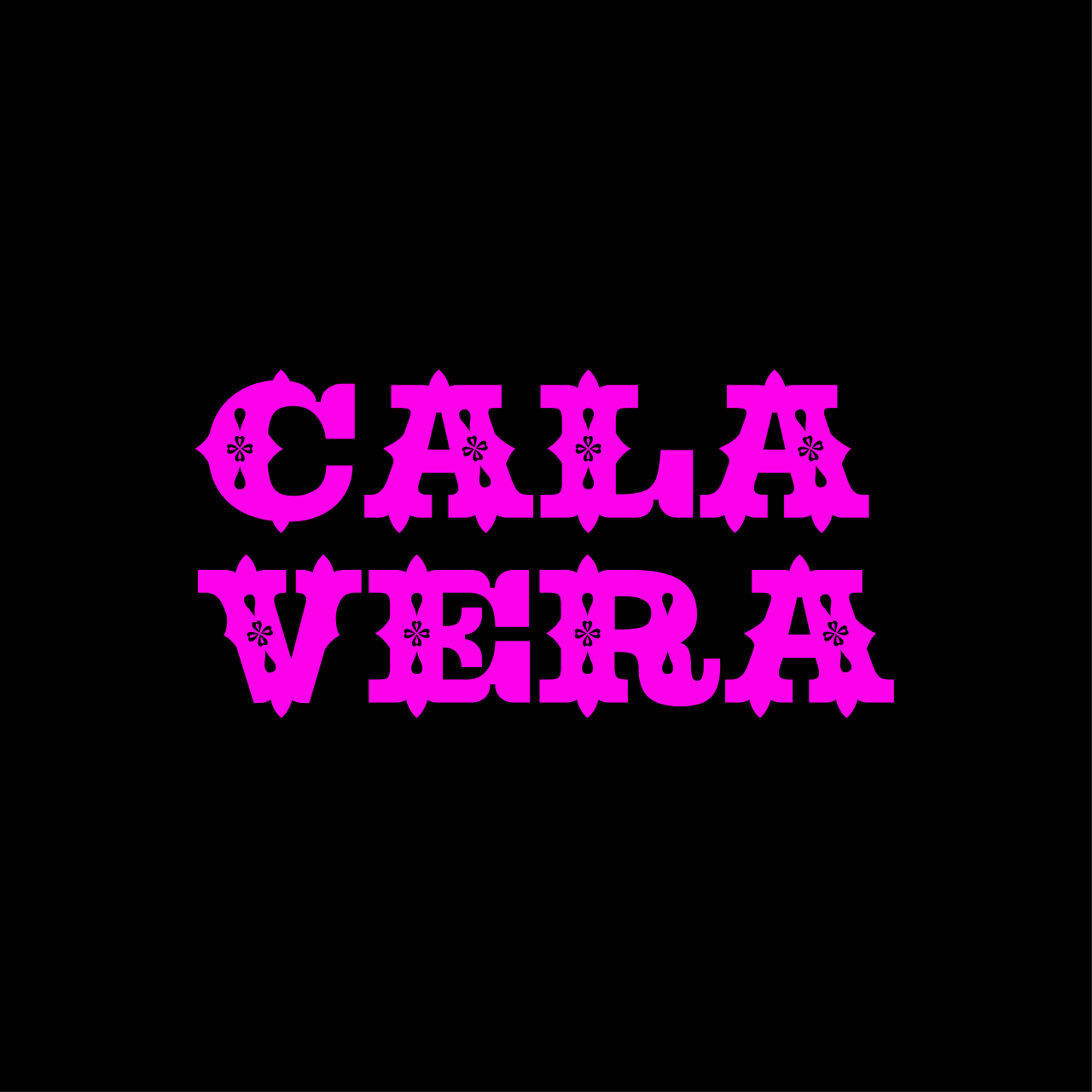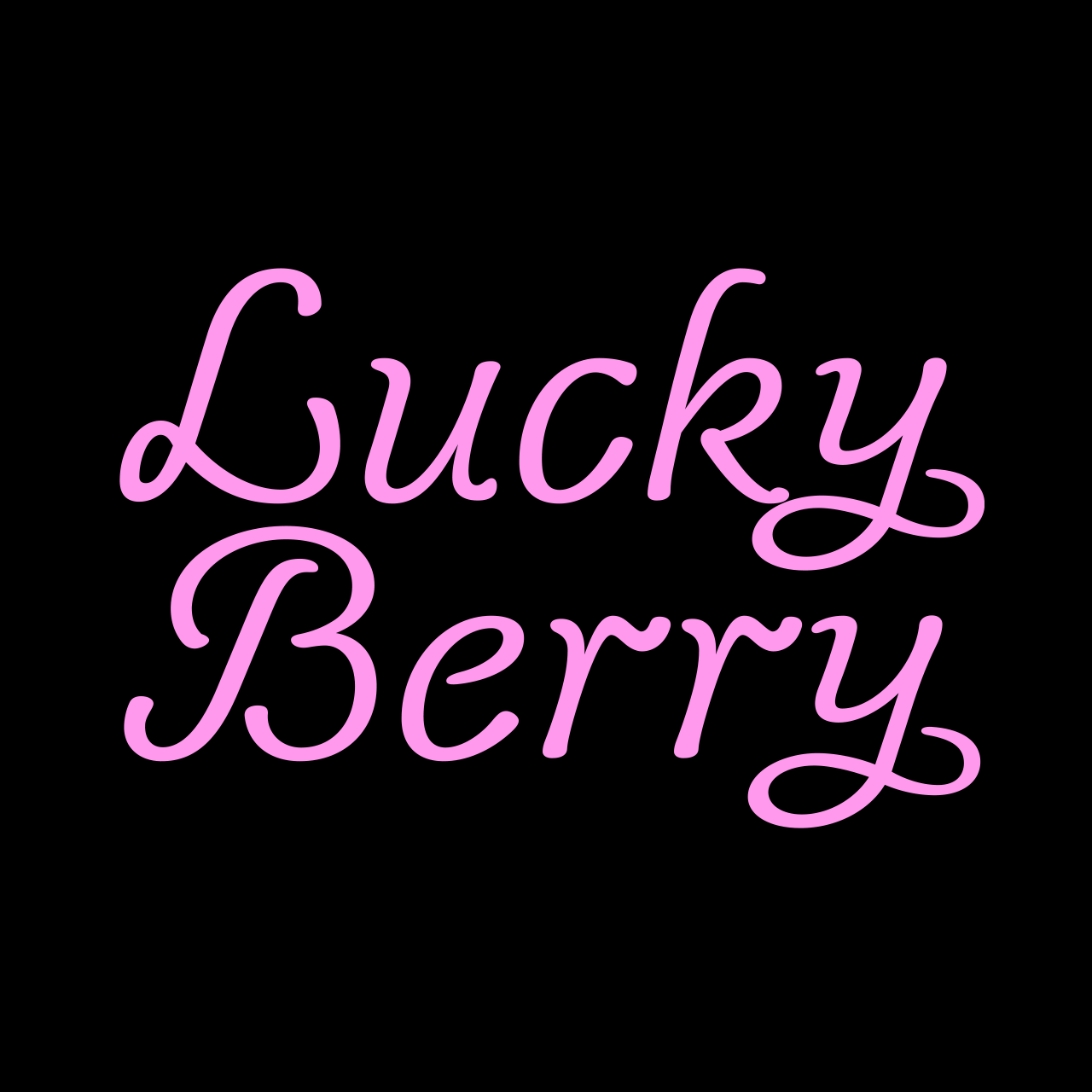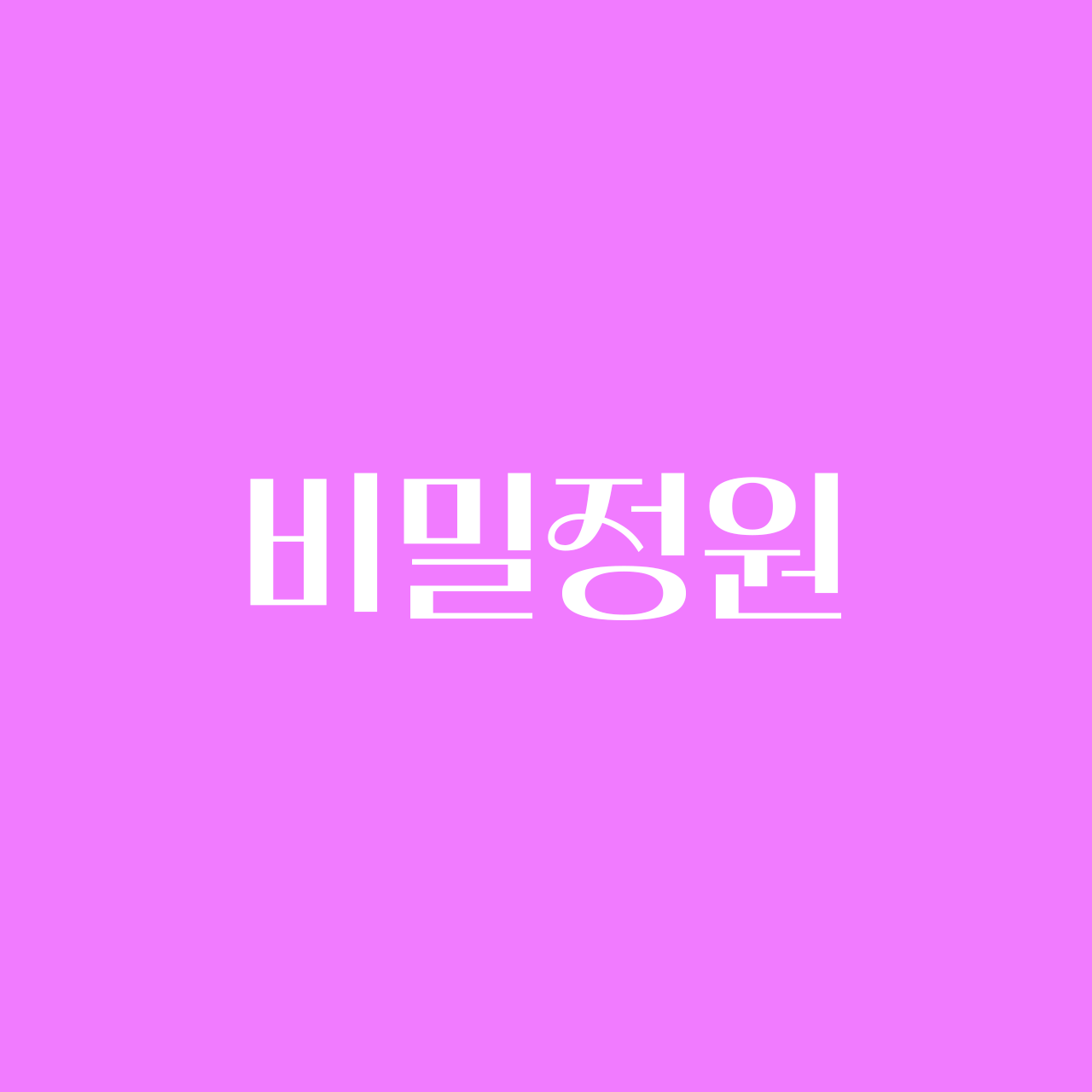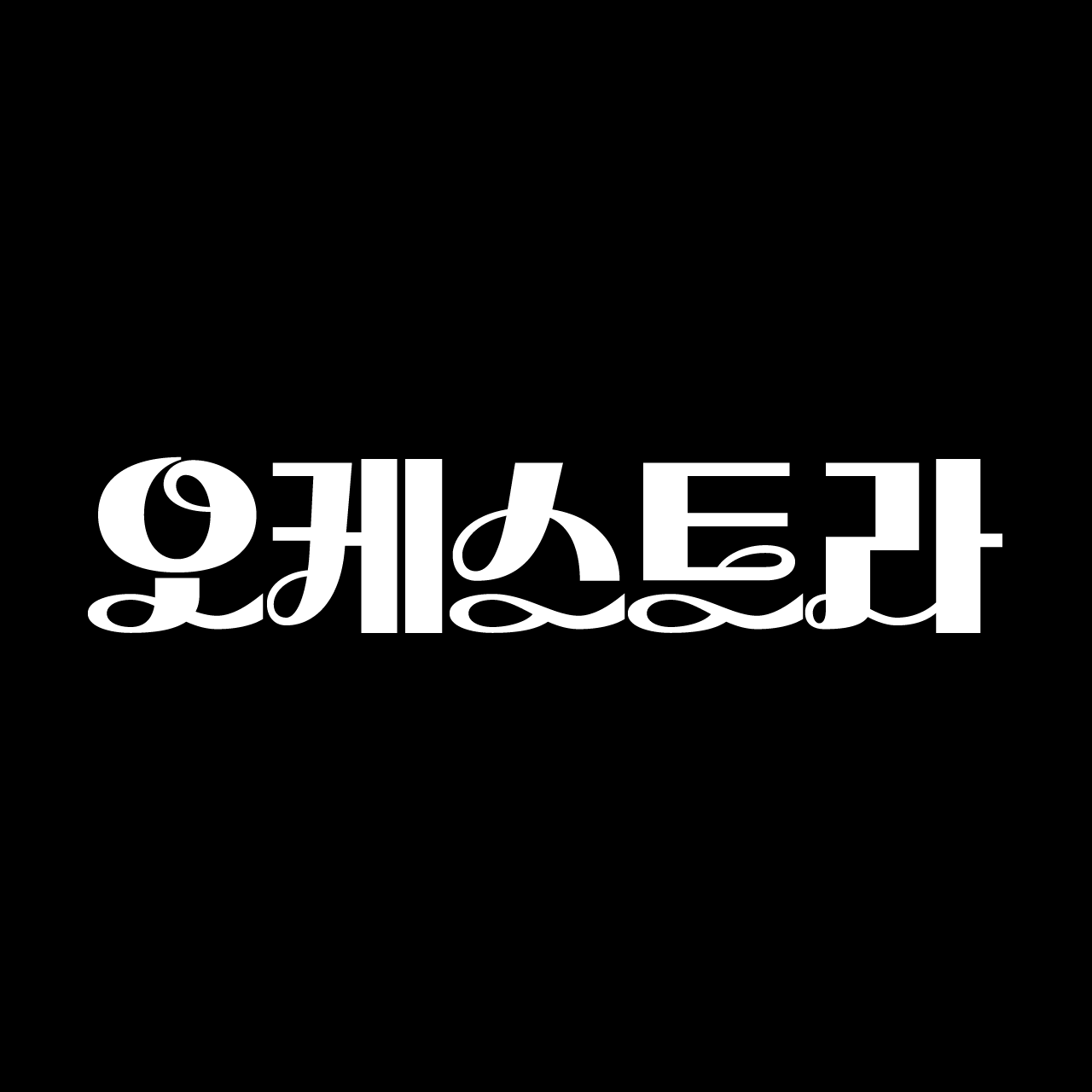
폰트로 완성하는 연말 분위기
연말연시 화려한 디스플레이 폰트 추천
연말 시즌을 더욱 빛내줄 특별한 디스플레이 폰트
크리스마스와 연말이 성큼 다가오고 있습니다.
연하장, 선물 패키지, 연말 캠페인 디자인을 준비 중이신가요?
화려하면서도 따뜻한 연말 분위기를 살리면서,
고급스러운 느낌을 더해 줄 폰트들로 디자인의 완성도를 높여 보세요.
고급스러운 분위기의 획대비 큰 폰트
연말이 다가오면, 한 해를 돌아보며 감사와 축하의 마음을 담은 디자인이 필요해지는데요.
이때, 디자이너들은 종종 고급스러운 분위기를 강조하기 위해 획대비가 큰 폰트를 선택하곤 합니다.
굵고 가는 부분의 대비가 뚜렷한 폰트는 세련된 느낌을 주며, 시각적으로도 강렬한 인상을 남기기 때문이죠.
어떤 디자인에서도 깊이 있는 매력을 발산하는 폰트들을 만나보세요!
산돌
안단테
「Sandoll 안단테」 는 클래식한 느낌을 살린 디스플레이 폰트입니다. 리듬감 있는 형태와 함께 획 대비가 큰 특징을 가지고 있어 고급스러운 연말 분위기를 강조하는 데 자주 사용되죠. 폰트명인 '안단테'는 음악 용어로 '느리게 연주하기'라는 뜻을 지니고 있으며, 형태에서는 영문 폰트인 Bodoni를 연상시키는 콘트라스트와 세리프가 돋보입니다. 이 폰트의 가장 큰 매력은 ㅁ, ㅂ, 그리고 받침 ㄴ의 아래쪽에 물결치듯 흐르는 곡선입니다. 이러한 곡선이 폰트에 부드럽고 유려한 느낌을 더해주는데요. 특히 클래식 음악 관련 공연 및 이벤트 포스터 등에 우아하고 세련된 분위기를 강조하는 폰트로 추천드립니다.
디자인210
210 비밀정원
「210 비밀정원」 은 최근 많은 사랑을 받고 있는 폰트로, 꽉 찬 모듈과 뚜렷한 획 대비가 세련되고 깔끔한 느낌을 줍니다. 특히 자소 'ㅅ, ㅈ, ㅊ'의 유연한 곡선은 독창적이며 유니크한 매력을 더해주죠. 가지런한 글줄이 안정감을 주어 문장에서도 가독성이 뛰어나며, 세 가지 굵기로 제공되어 다양한 디자인에 활용할 수 있습니다. 포스터, 패키지 디자인, 영상 등에서 신비롭고 몽환적인 분위기를 연출하는 데 잘 어울립니다.
시선을 사로잡는 맥시멀리즘 폰트
연말 분위기는 고급스럽게도, 또는 화려하게도 연출할 수 있죠.
디자인에 색다른 느낌을 주고 싶다면 화려한 폰트를 선택해 보는 건 어떨까요?
폰트 하나만으로도 분위기를 완전히 바꿀 수 있는 매력을 느껴보세요!
윤디자인
DS 엉뚱상상 Variable
윤디자인의 「DS 엉뚱상상 Variable」 은 디자이너의 실험 정신을 자극하는 배리어블 폰트입니다. 이 폰트는 별과 꽃 모양으로 처리한 속공간과 같은 장식적인 요소들, 그리고 ㅅ, ㄹ 자소들의 재치있는 표현들이 눈길을 사로잡으며, 다양한 굵기가 섞여 있어 독특하고 다채로운 디자인을 연출할 수 있습니다. 기하학적인 그래픽과 결합하면, 정말 다이내믹한 효과를 만들어낼 수 있겠죠? 특히 연말연시의 화려한 파티나 축제 디자인에 잘 어울리니, 배리어블 축을 이리저리 조절해 보며 가능성을 마음껏 펼쳐보세요!
산돌
SD 피쉬테일
「SD 피쉬테일」 은 빅토리아 시대 토스카나 양식 레터링에서 영감을 받은 독특하고 화려한 디자인이 특징인 폰트입니다. 물고기의 꼬리를 닮은 획 끝 장식이 돋보이며, 3가지 웨이트로 다양한 분위기를 연출할 수 있습니다. 특히 가장 굵은 Heavy 웨이트에는 보다 더 장식적인 요소를 가미한 Inline과 Shadow 스타일을 더해 더욱 화려한 룩을 제공합니다. 독특한 비주얼이 요구되는 디자인에서 눈에 띄는 요소로 활용하기 좋으며, 다양한 디자인에 신선한 매력을 부여할 수 있는 추천 폰트입니다.
우아한 라틴 필기체 폰트
연말 디자인에 우아함을 더하기 위해, 라틴 필기체 폰트가 사용되는 것을 자주 볼 수 있는데요.
곡선이 살아있는 부드럽고 클래식한 필기체 폰트는 어떠한 문구도 품격 있게 표현해줄 수 있죠. 한번 알아볼까요?
더타입파운더스
Aphrodite
더타입파운더스의 「Aphrodite」는 라틴 캘리그래피의 아름다움을 느낄 수 있는 폰트입니다. 이 폰트는 뾰족한 모양의 펜촉으로 쓰여진 캘리그라피 스타일을 잘 보여주고 있는데요, 가는 선과 굵은 선의 강한 대비와 유려한 곡선이 특징입니다. 이 스타일은 고급스럽고 섬세한 느낌을 주어 청첩장, 파티 초대장, 고급 레스토랑 메뉴판, 기념일 카드 등에서 자주 사용되죠. 「Aphrodite」는 글자마다 다양한 대체 글립이 구비되어 있어, 깔끔한 인상부터 극강의 화려함까지, 표현할 수 있는 스펙트럼이 다양합니다. 장식적인 곡선이 이리저리 교차되는 모습을 활용해 화려함을 강조해 보는 건 어떨까요?
코스모프타입
CT LuckyBerry
코스모프타입의 「CT LuckyBerry」 는 캐주얼하고 귀여운 인상을 주는 라틴 스크립트 폰트로, 이탤릭 스크립트 스타일을 현대적으로 재해석한 폰트입니다. 균일한 획 굵기 덕분에 부드럽고 자연스러운 필기 느낌을 연출하며, 편안하고 친근한 분위기를 전달하는 것이 특징입니다. 이러한 요소들 덕분에 「CT LuckyBerry」는 밝고 경쾌한 디자인에 어울리며, 브랜딩, SNS 그래픽 같은 프로젝트에 사용해 보시길 추천드립니다!
지금까지 연말연시 분위기에 어울리는 화려한 디스플레이 폰트를 소개해드렸습니다.
다가오는 연말, 다양한 디자인에서 매력적인 폰트들이 빛을 발하는 모습을 기대해봅니다.